Quando un font riesce a definire un brand: Dior (e gli altri) tra tipografia e potere
Da Celine a Balenciaga, da Gucci a Burberry. Il logo è una forma di coerenza quasi totemica, che diventa strumento di identità culturale, strategia estetica e posizionamento politico. Ecco una lettura del fenomeno del rebranding che passa dal cambiamento del font
Cambiare font significa, di fatto, cambiare pelle. È un gesto che scarta un involucro identitario sedimentato nel tempo per sostituirlo con un nuovo strato, capace di riscrivere ciò che un marchio vuole comunicare al mondo. Le maison storiche nate nel Novecento lo sanno bene: dopo decenni a presentarsi con la stessa silhouette tipografica, il reset appare oggi come una delle strategie più radicali e insieme più pragmatiche per riorientare la propria aura.
Brand e nuovi volti, l’importanza del font
Modificare un carattere non equivale semplicemente ad aggiornare un logo: significa riaffermare o negoziare un posizionamento culturale, spostare l’immaginario, insinuare un’idea di modernità, aprire nuove traiettorie estetiche e politiche. Così, quando anche Dior sceglie di intervenire sulla propria identità tipografica, il gesto non parla soltanto di stile, ma di potere narrativo e di come il branding contemporaneo sia diventato un linguaggio capace di orientare percezioni, discorsi e desideri collettivi. Fino a pochi anni fa, il rebranding – quell’insieme di operazioni strategiche pensate per riposizionare un marchio nel medio-lungo periodo – si traduceva soprattutto in un nuovo logo, in una diversa strategia di comunicazione o, al massimo, in una revisione dell’immaginario visivo. Oggi il cambio font è entrato stabilmente in questo processo: non è più un dettaglio tecnico, ma un gesto identitario spesso deliberato e sempre più frequente. Dopo aver analizzato mercato e competitor, i brand valutano se una riscrittura dell’identità sia necessaria, perché il pubblico è cambiato, perché si vuole intercettare un nuovo desiderio culturale, oppure perché un nuovo direttore creativo intende impostare un reset radicale. E poco importa se la maison deciderà di raccontare apertamente questa trasformazione o di farla scorrere in silenzio. Ciò che davvero conta è la nuova copertina del libro, da cui ricominciare a scrivere un nuovo capitolo.
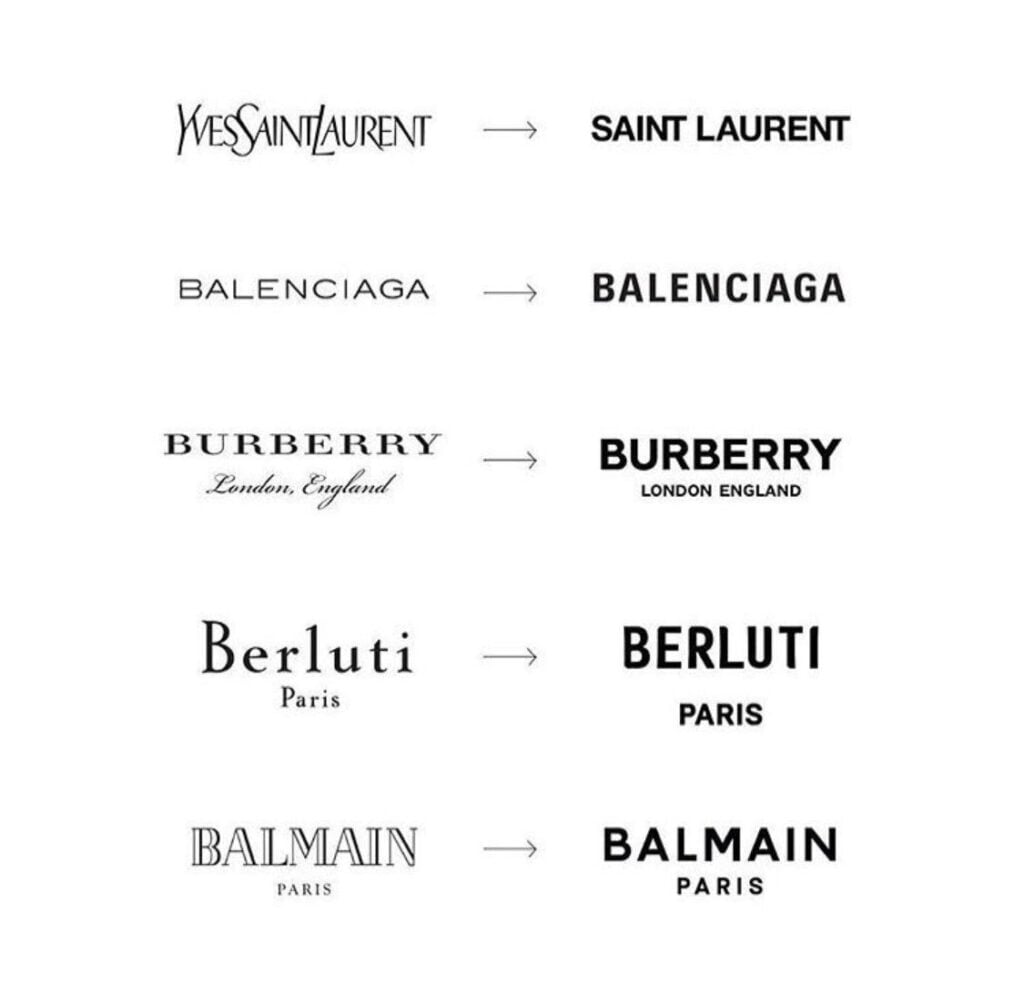
Le trasformazioni più radicali dei loghi dei brand passano anche per i font
Tra le rivoluzioni tipografiche più discusse spicca quella di Yves Saint Laurent. All’arrivo di Hedi Slimane alla direzione creativa nel 2012, la decisione di intervenire sull’identità visiva del brand generò polemiche accese: non solo un nuovo font, ma soprattutto l’eliminazione del nome “Yves” dal logo. Un gesto che, a una prima lettura, sembrava un affronto alla memoria del fondatore. Eppure la scelta di Slimane affondava le radici proprio nella storia della maison. Il logo “Saint Laurent” riprendeva quello della linea prêt-à-porter lanciata nel 1966, “Saint Laurent Rive Gauche”. Lungi dall’essere una cancellazione, fu un gesto filologico che riportava l’identità visiva al momento più rivoluzionario del brand. Una scelta che, ancora oggi, molti faticano a perdonare. Nel 2015 toccò a Gucci, ma questa volta l’esperimento riuscì. Senza il peso di un nome fondatore nel logo, Alessandro Michele – appena nominato direttore creativo – decise di avviare una trasformazione radicale. La sua “Guccification”, volta a ridefinire il linguaggio visivo della maison, passava anche dall’adozione del carattere Granjon Roman, più autorevole e classico. Una scelta perfettamente coerente con la sua estetica storicista e ipercitazionista.
Altri casi emblematici sul rebranding attraverso il font
Emblematico anche il caso Burberry: nel 2018 Riccardo Tisci affidò al grafico Peter Saville il nuovo logo e un monogramma inedito, presentati su Instagram. L’icona equestre venne abbandonata a favore di un sans-serif iper-minimal che, nel 2022, fu ulteriormente stilizzato dal successore Daniel Lee con un ritorno al serif d’archivio – segno di quanto la tipografia sia ormai diventata un vero campo di battaglia identitario. Sempre nel 2018, Hedi Slimane – ormai avvezzo alle rivoluzioni visive – intervenne su Celine: eliminò l’accento dalla “E” e snellì il font. Un aggiornamento che scatenò un’ondata nostalgica ancora viva, come testimonia la community social dei fan del “vecchio Celine” (cercare alla voce @oldceline sui social). Anche Balmain si è orientato verso un logo più rigoroso e minimalista, introdotto da Olivier Rousteing per accompagnare il nuovo corso internazionale del brand e sottolineare il lancio della collezione maschile. Insomma, i casi sono tanti. E la spinta verso una maggiore riconoscibilità globale non passa solo dalla tipografia, ma anche dall’alleggerimento dei nomi stessi: così Salvatore Ferragamo è diventato semplicemente Ferragamo, ed Ermenegildo Zegna è diventato Zegna.
Dior e l’ultima tendenza: tornare alle origini
Christian Dior merita una storia a parte. Il logo della maison, basato sul carattere Cochin del 1912, incarnava l’eleganza delicata che il couturier riteneva essenziale. Nel corso dei decenni è stato ritoccato solo un paio di volte, l’ultima nel 2018, mantenendo fino a poche settimane fa la scritta “DIOR” in maiuscolo. Con l’arrivo di Jonathan Anderson, la trasformazione non passa però da un azzeramento totale, ma da un ritorno consapevole; il Cochin torna al centro dell’identità visiva con una D maiuscola seguita da minuscole oblique e sottili. Un gesto controcorrente, ma perfettamente coerente con il suo motto: decodificare per ricodificare. Prima si eliminano i segni ridondanti, poi si riassemblano i codici – couture, artigianato, tipografia – in un equilibrio nuovo ma rispettoso delle radici. La domanda che resta è se questa sia la nuova frontiera: non più correre verso l’iper-modernità, ma riconnettersi alla propria grammatica originaria. Dior sembra crederci, scegliendo una via che non è soltanto stilistica, ma profondamente allineata al proprio patrimonio culturale.
Rebranding, ma forse omologazione?
Negli ultimi anni il (re)branding si è sdoppiato: da un lato la ricerca di identità distintive, dall’altro la tendenza alla semplificazione uniforme, il cosiddetto blanding. Quest’ultimo è il risultato di esigenze pratiche e culturali: leggibilità digitale, appetibilità verso mercati globali e più di una generazione che preferisce marchi meno “urlanti”. Millennial e Gen Z, presente e futuro del mercato del lusso, sono infatti generazioni no-logo. Cresciute in un eccesso di segni e marchi, preferiscono oggi codici visivi più silenziosi, personalizzabili, meno gerarchici. Per parlare a loro, molti brand hanno sacrificato complessità e storicità in favore di un’estetica neutra e funzionale. Ma uniformità non significa necessariamente povertà progettuale: molti direttori creativi scavano negli archivi, intrecciano riferimenti e usano la semplicità per far brillare altri segni distintivi. Il font, dunque, non è un dettaglio tecnico, ma un tassello narrativo. E, come in ogni cosa, è la coerenza a fare la differenza. In un mercato che cambia rapidamente – e vive soprattutto online – la vera sfida per le maison è restare leggibili senza perdere rilevanza, aggiornare il linguaggio senza snaturare ciò che le rende uniche.